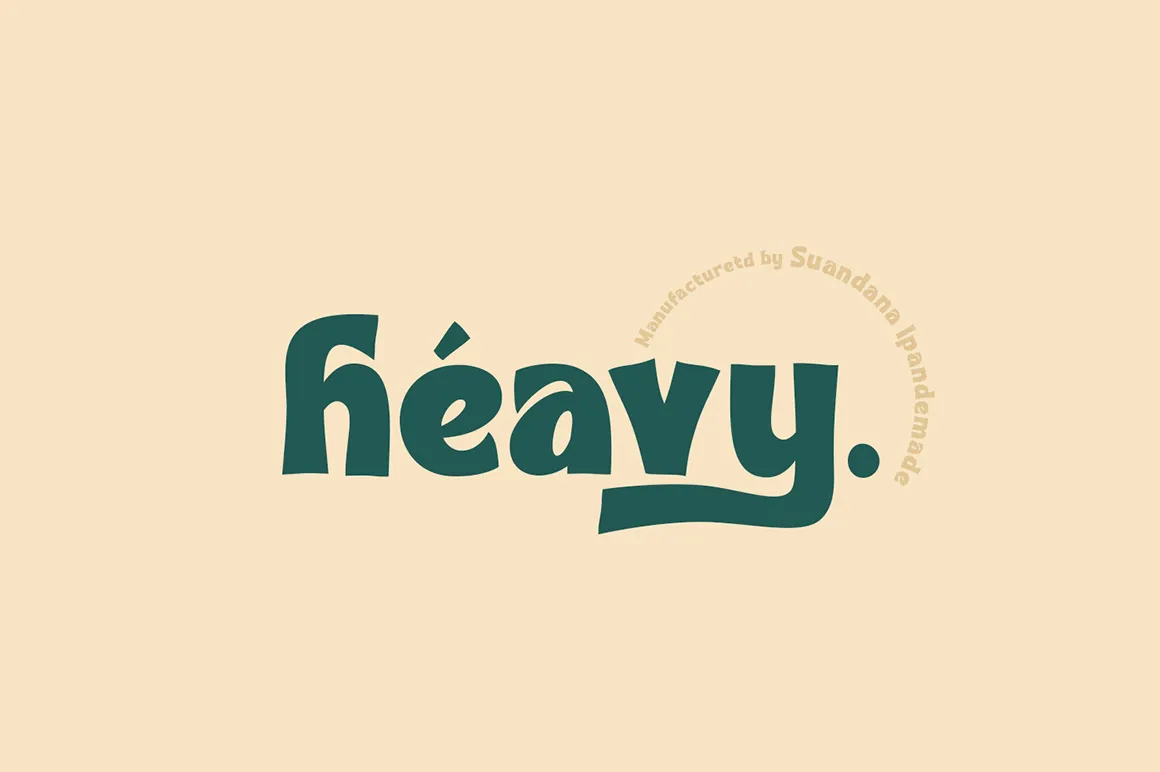
A fonte Heavy Bold Font é a escolha perfeita para adicionar um toque de diversão aos seus materiais digitais. Feita especialmente para quem gosta de uma linguagem chamativa e fortes, essa font garante que seu design se destaque da lota. Ideal para uso em livros, marcações de capa, embalagens de produtos, convites, citações, camisetas, rótulos, outdoors ou logotipos, Heavy Bold Font é uma ferramenta versátil para qualquer projeto visual. Feita pelo designer madeDeduk, esta font oferece uma combinação única entre força e frescura. Seu design bold é perfeito para quando você quer transmitir a mensagem de maneira assertiva, mas também garantir que ela seja visível e memorável. Perfect para um toque diferente em seu próximo projeto gráfico, Heavy Bold Font está aqui para ajudá-lo a destacar sua criação com estilo.